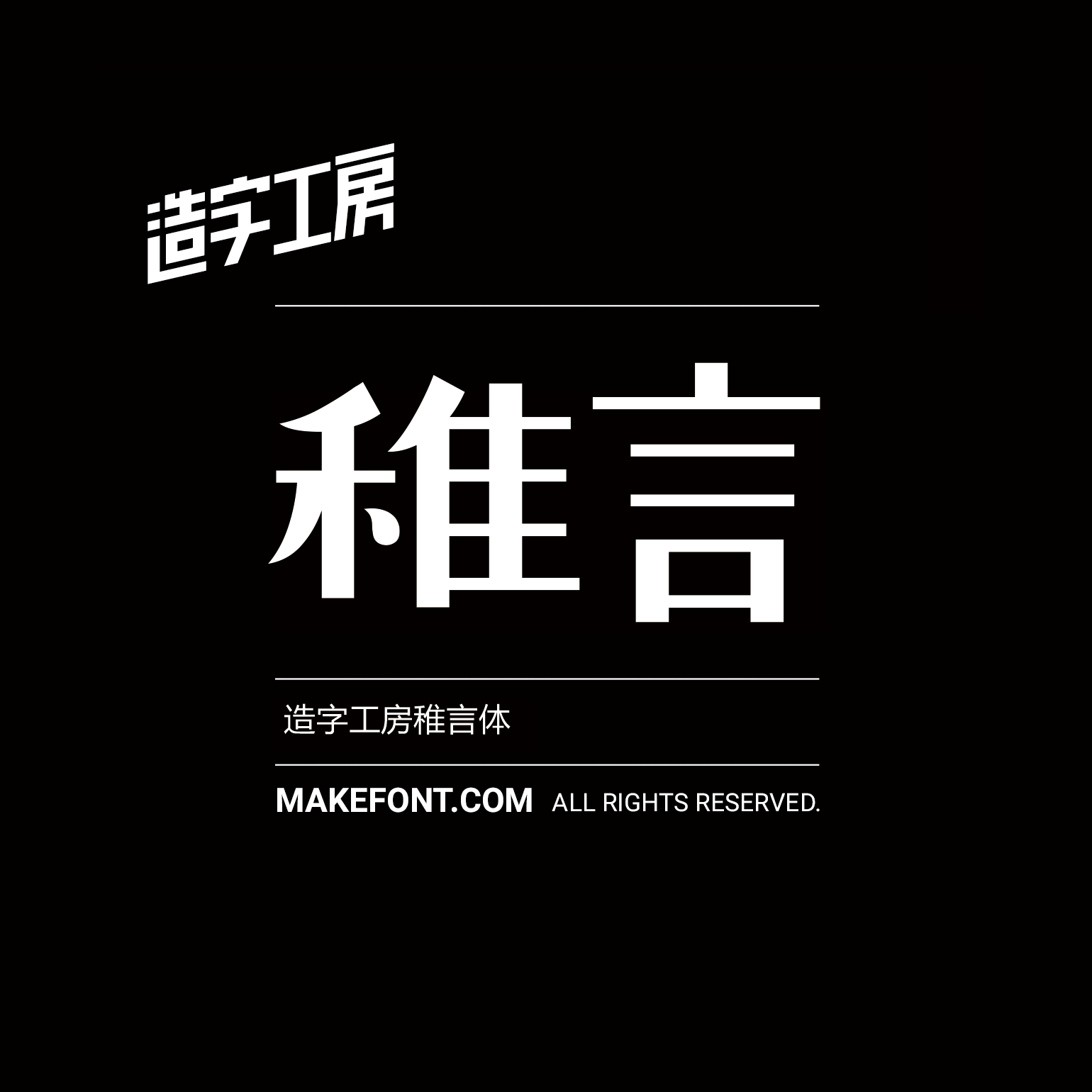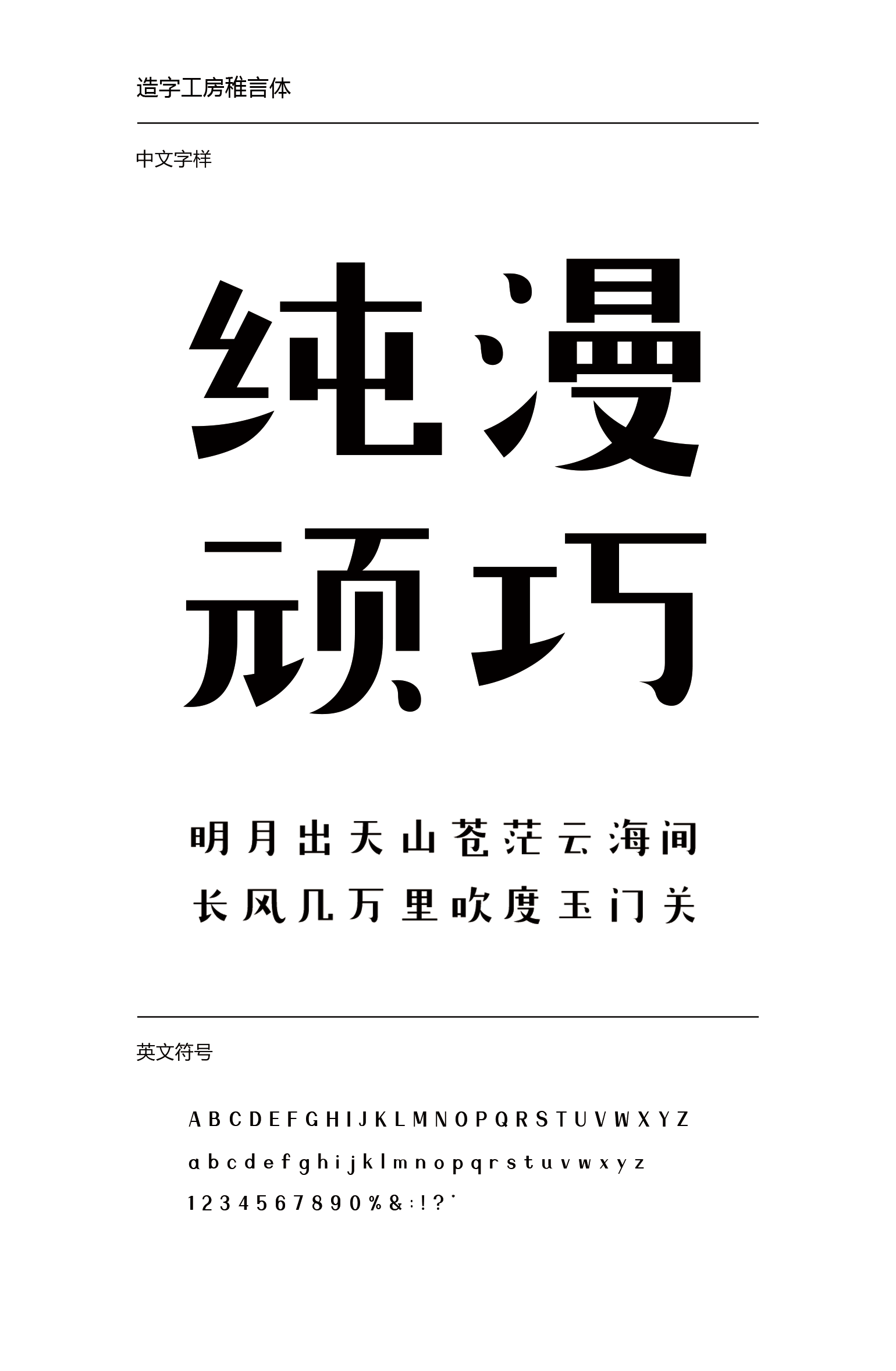
造字工房稚言体设计说明
造字工房稚言体字型设计随性,笔画舒展有力,结体宽扁却不粗臃。左右部件参差错落,却不失平衡之感,多处创新处理令其节奏感更强,更加灵动充满张力。适用于大标题及个性品牌设计推广等环境。本字体为简体字库,采用OpenType/CID格式,Adobe-GB1-5编码。基于中华人民共和国GB2312-80字符集标准,另按需添加101个汉字。共收容字数6864CJK汉字,ASCII常用字符100个。